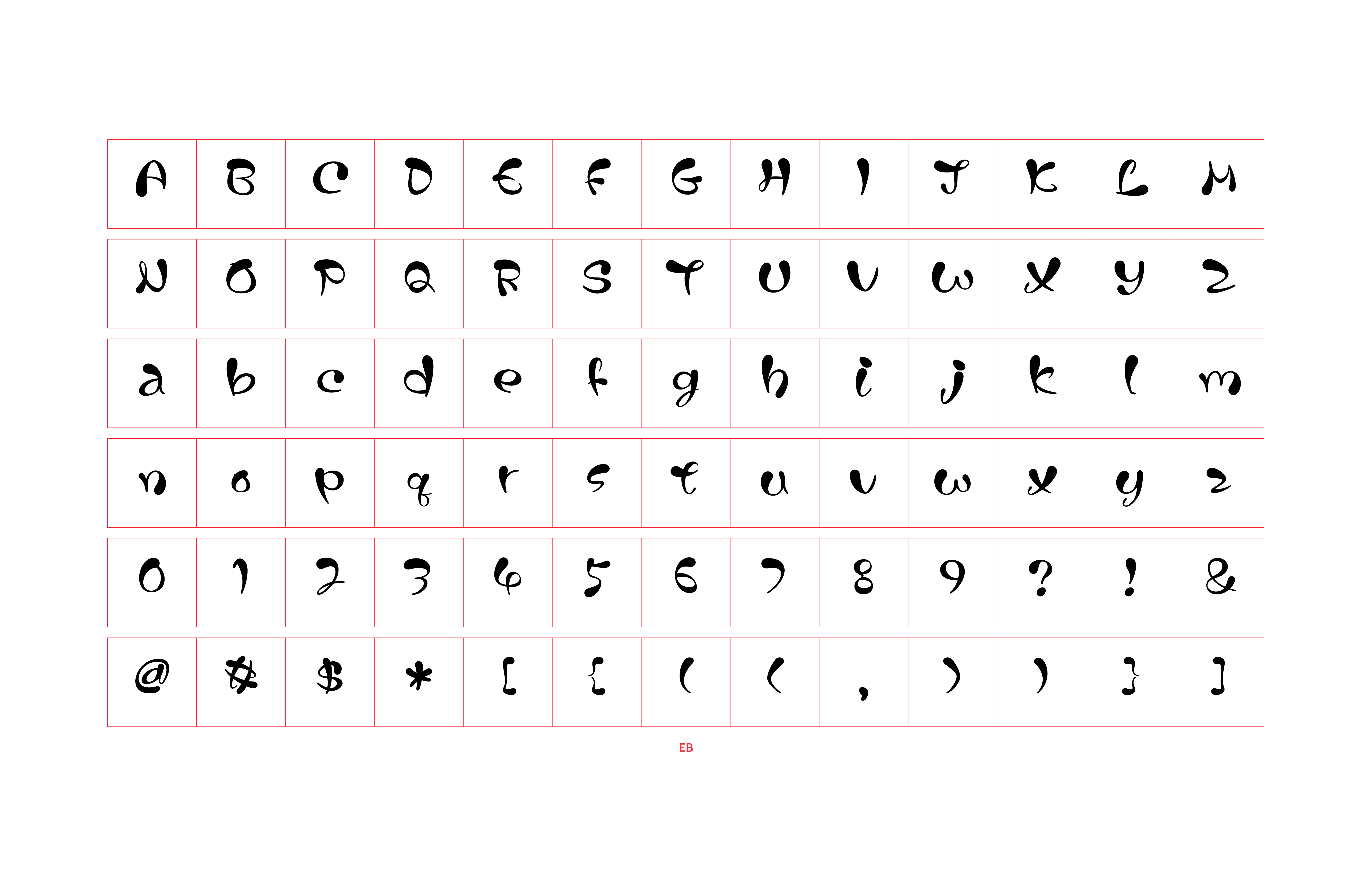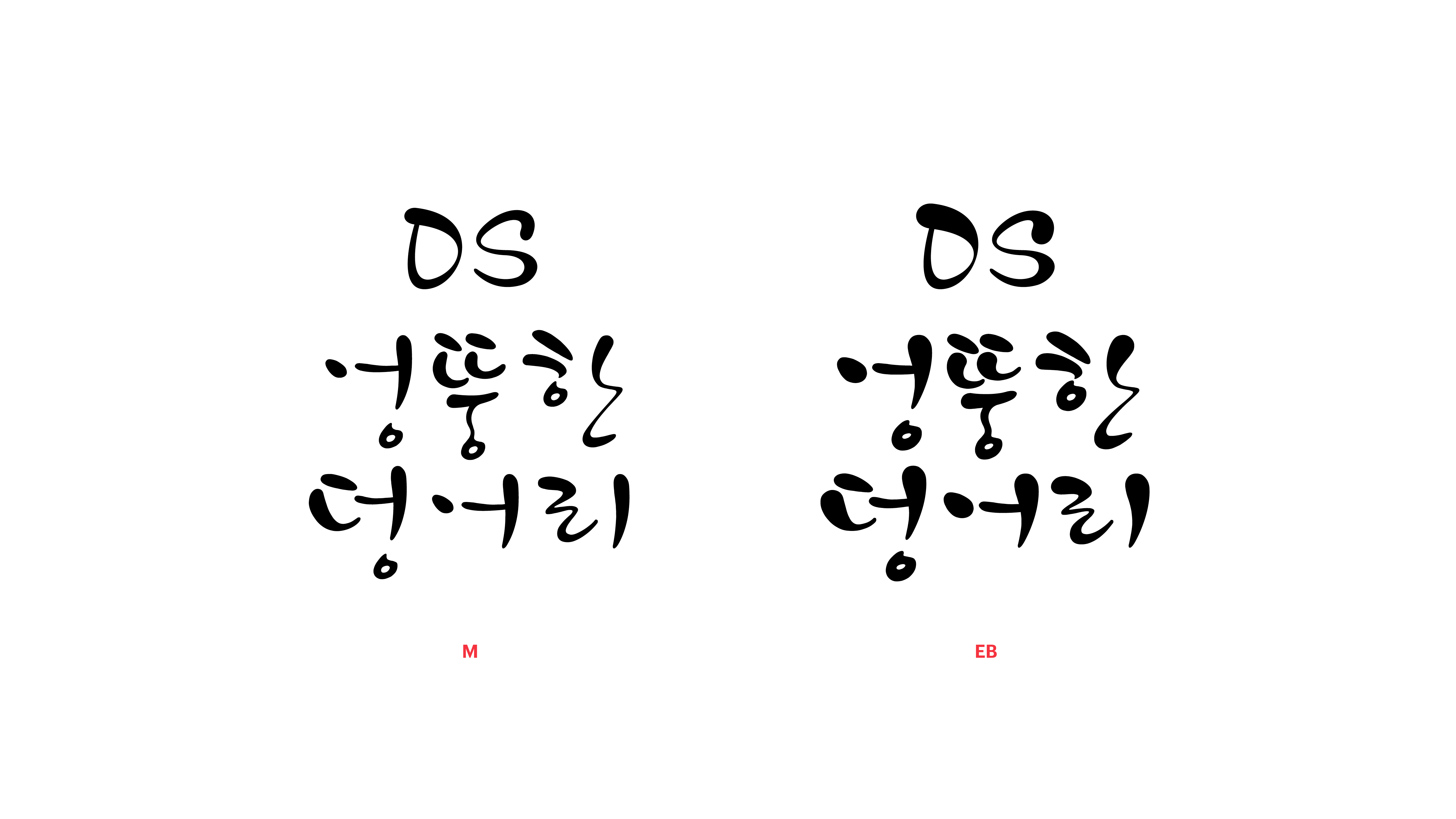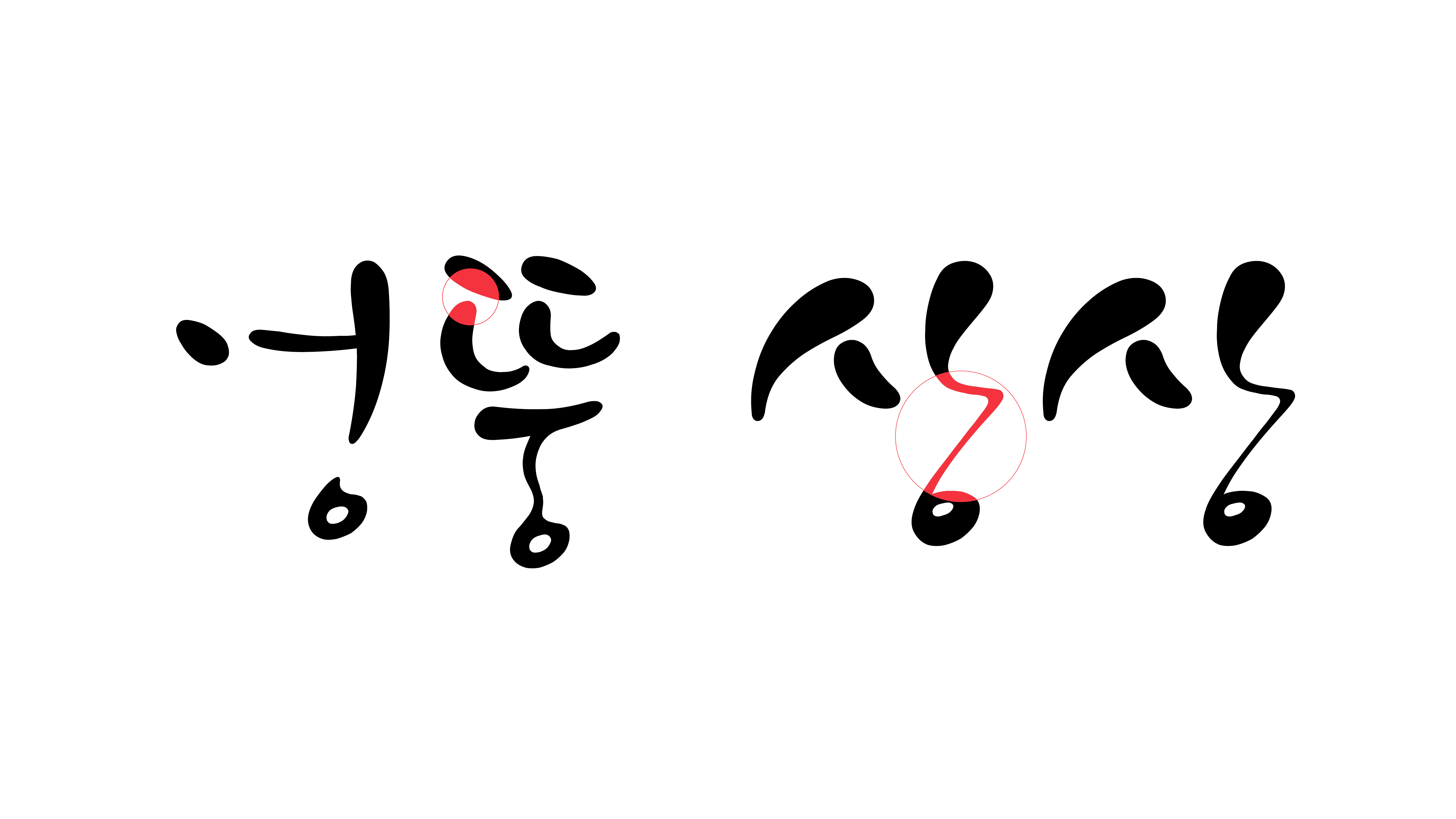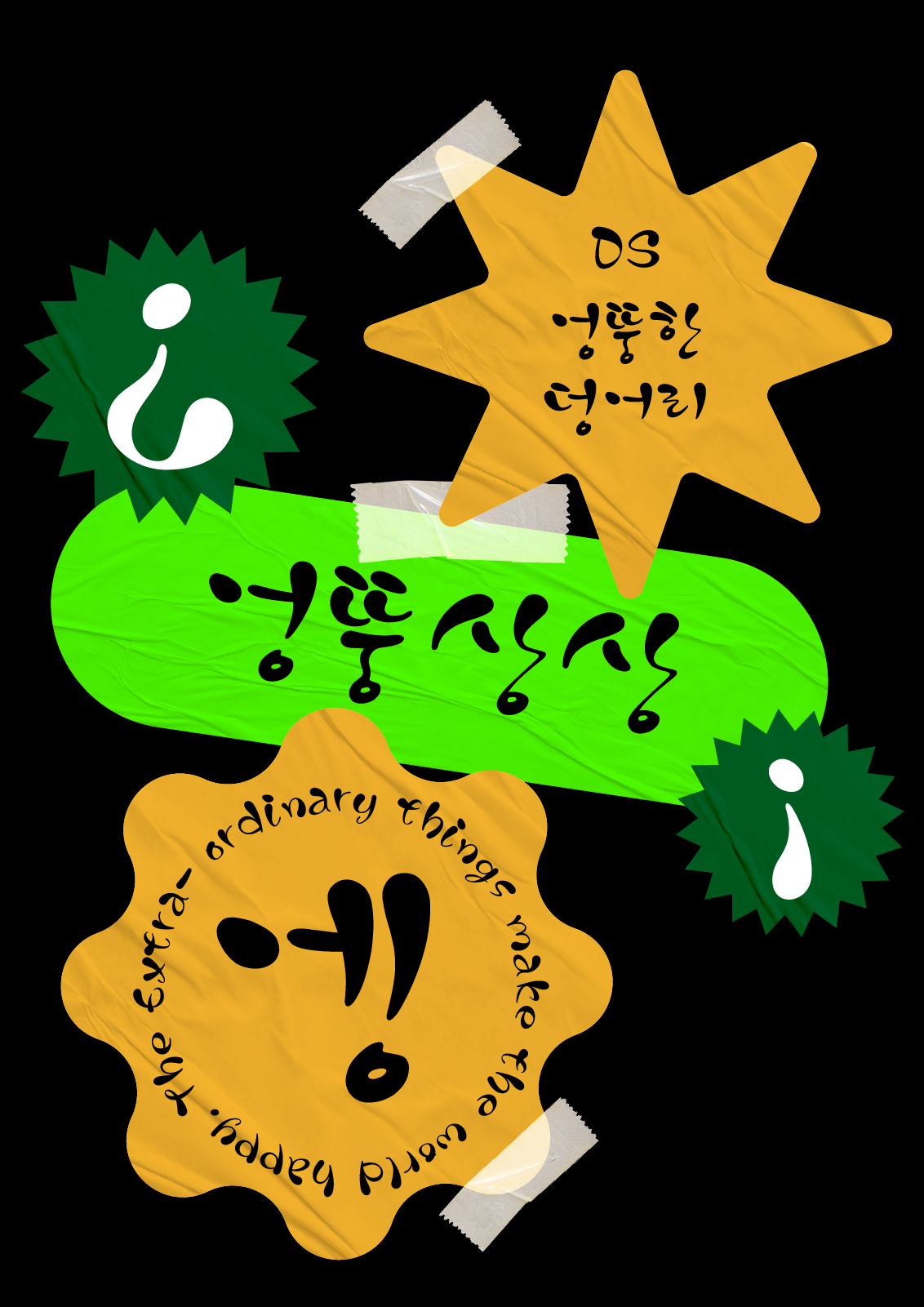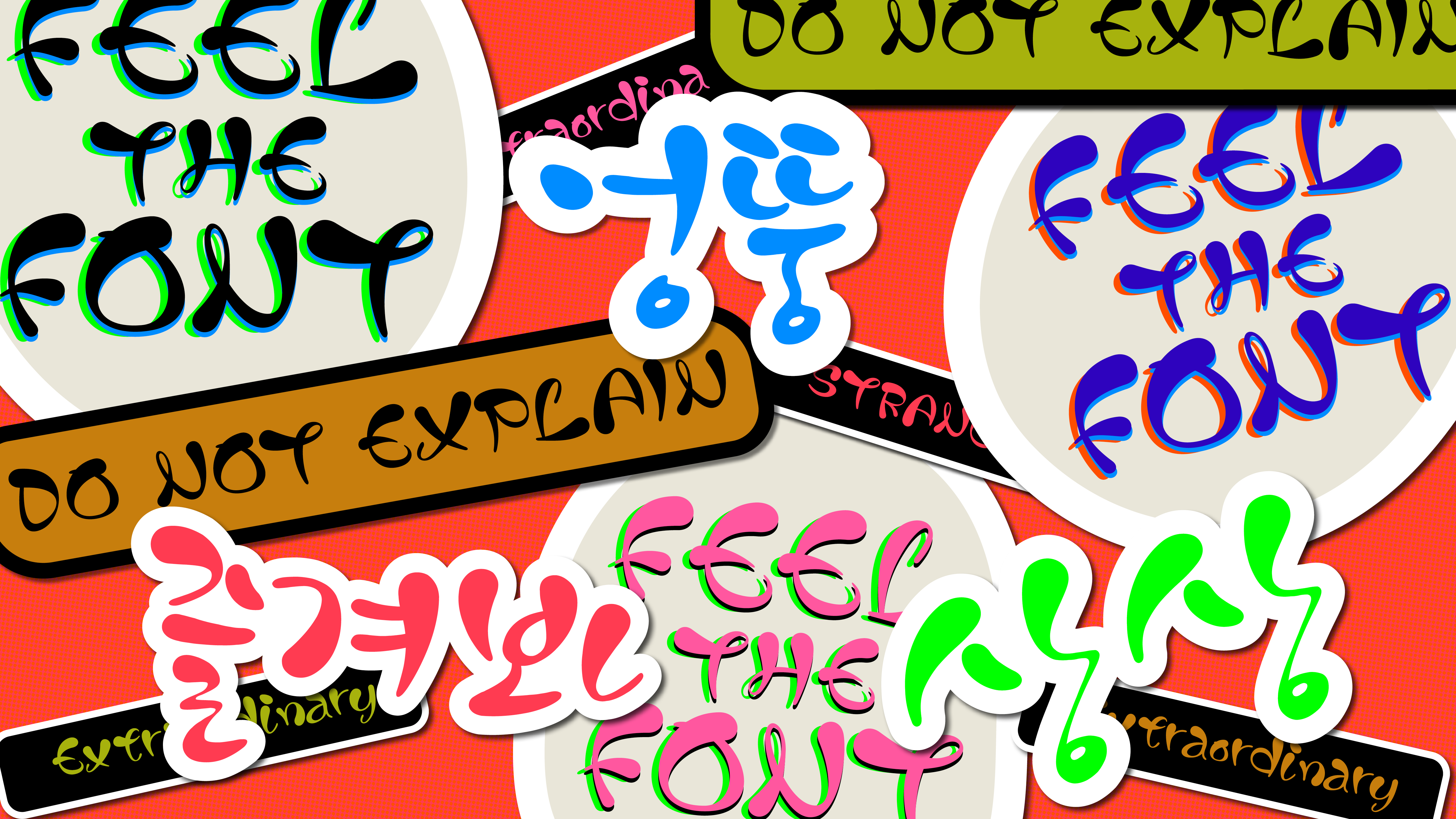
DS엉뚱한 덩어리
Yoon DS엉뚱한 덩어리
엉뚱한 것들은 세상을 즐겁게 합니다. 마치 폰코 자키처럼 말이죠! 그러니 우리가 멍 때릴 때 하는 뜬구름 잡는 상상을 이 폰트로 기록해보세요. 잉크를 가득 머금은 붓이 그려내는 도톰한 획처럼, 시작부터 꽤 굵직하고 근사할지도 모르잖아요?